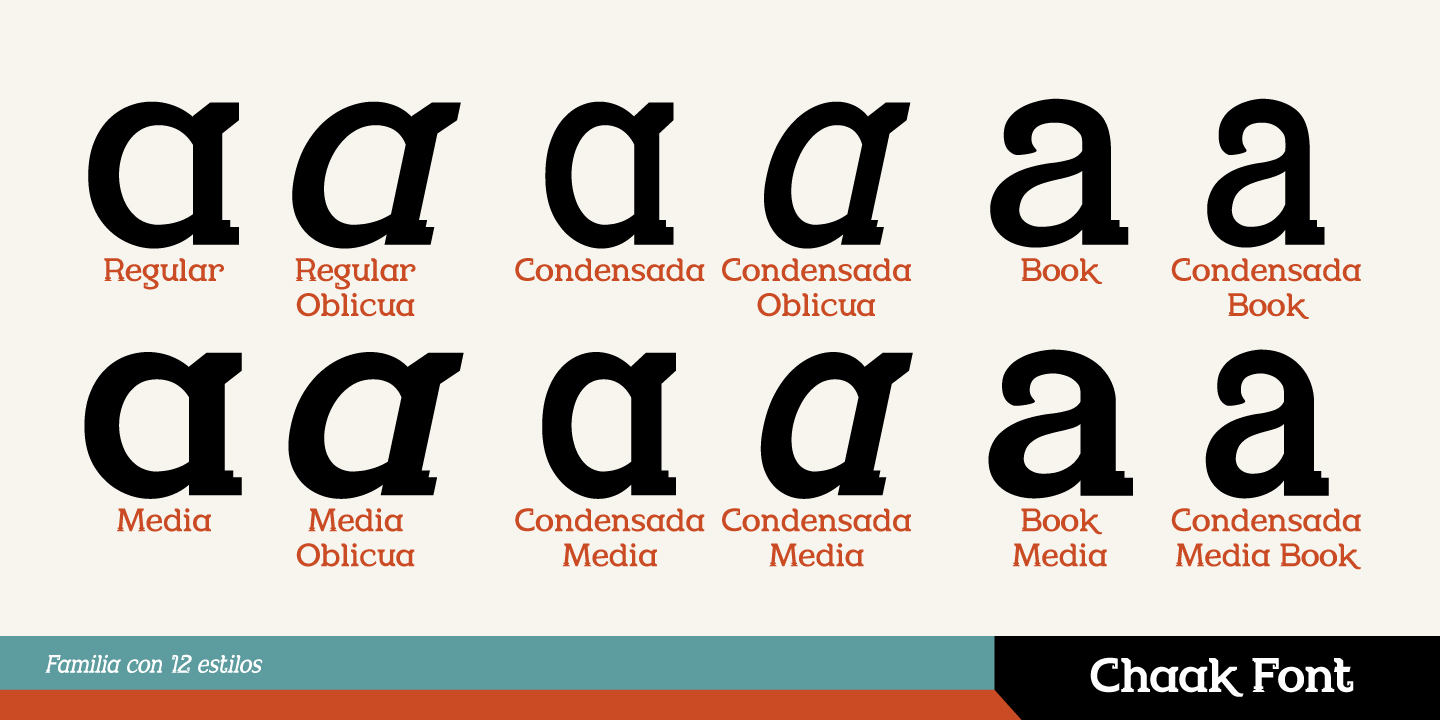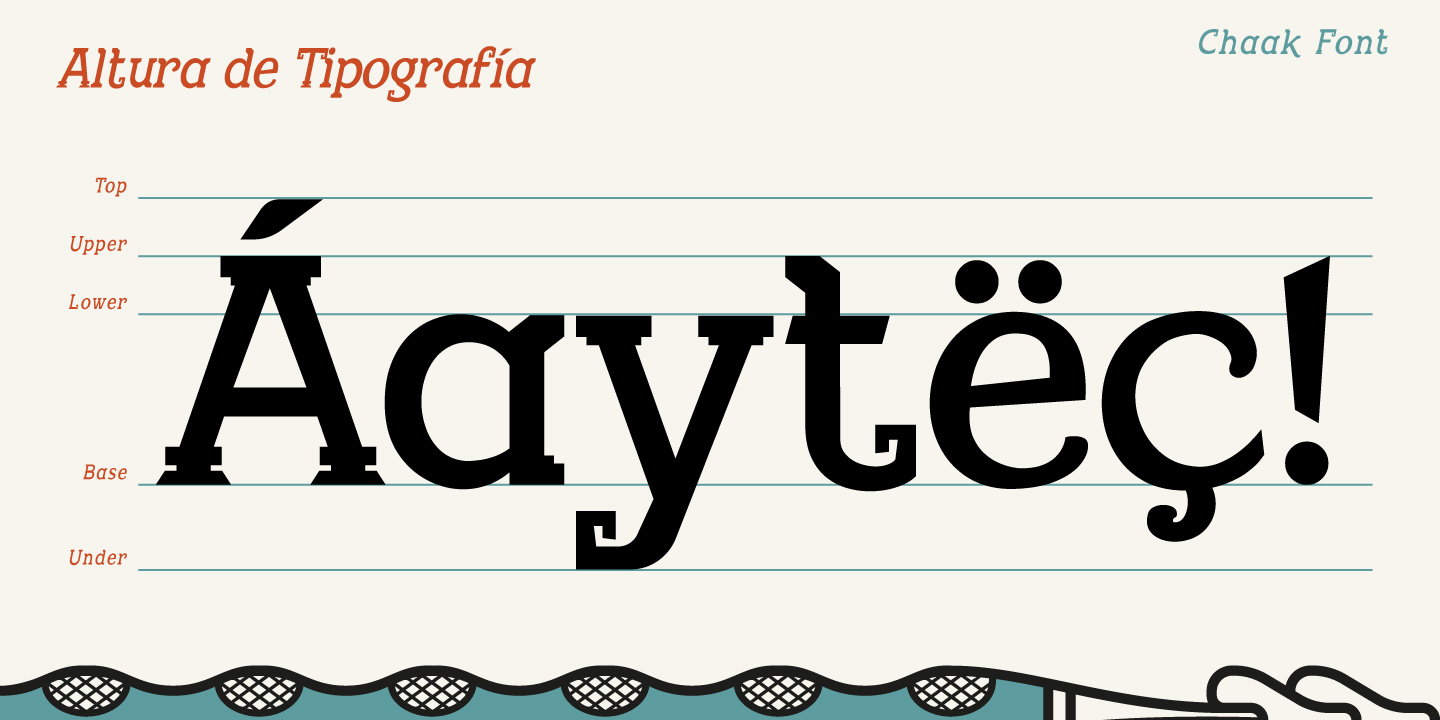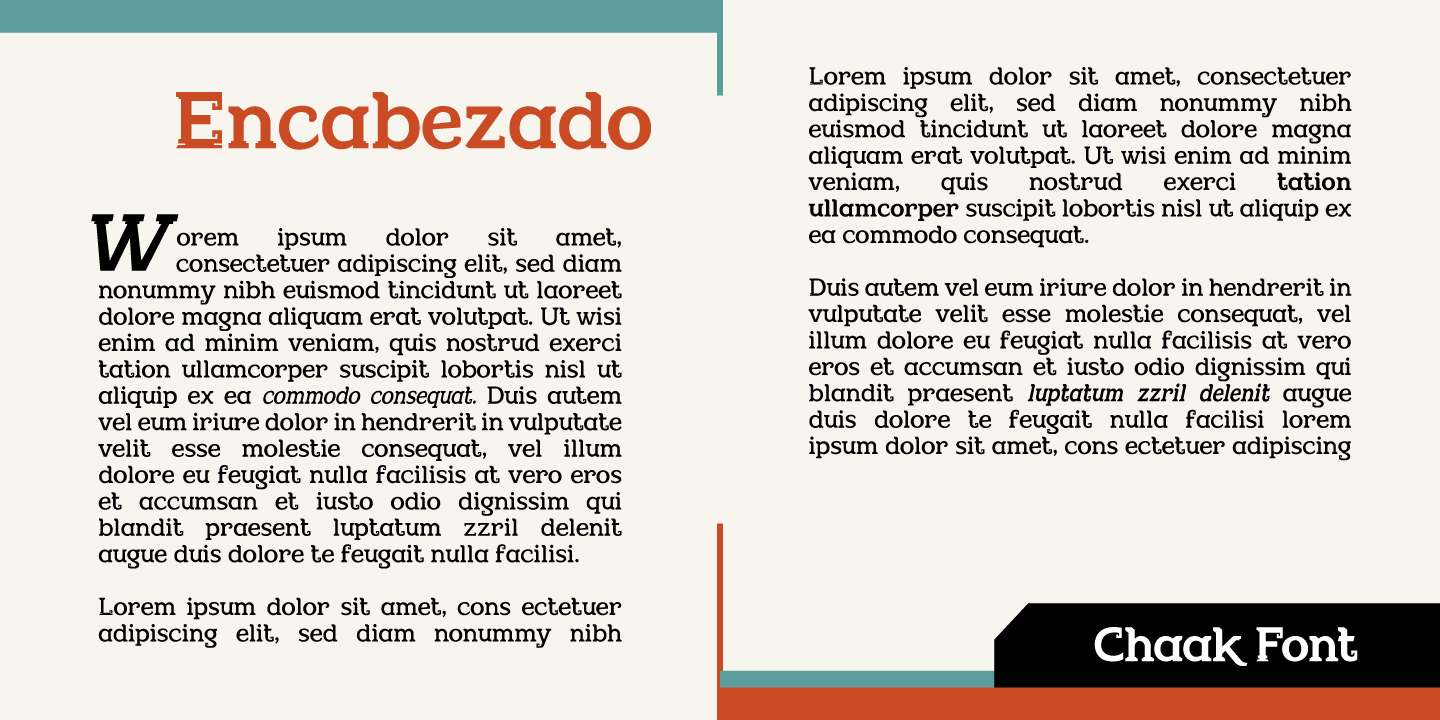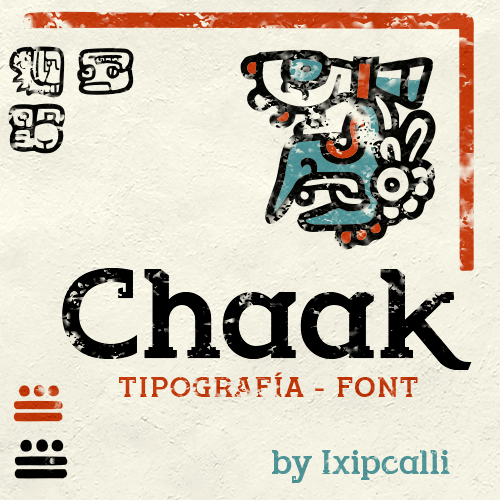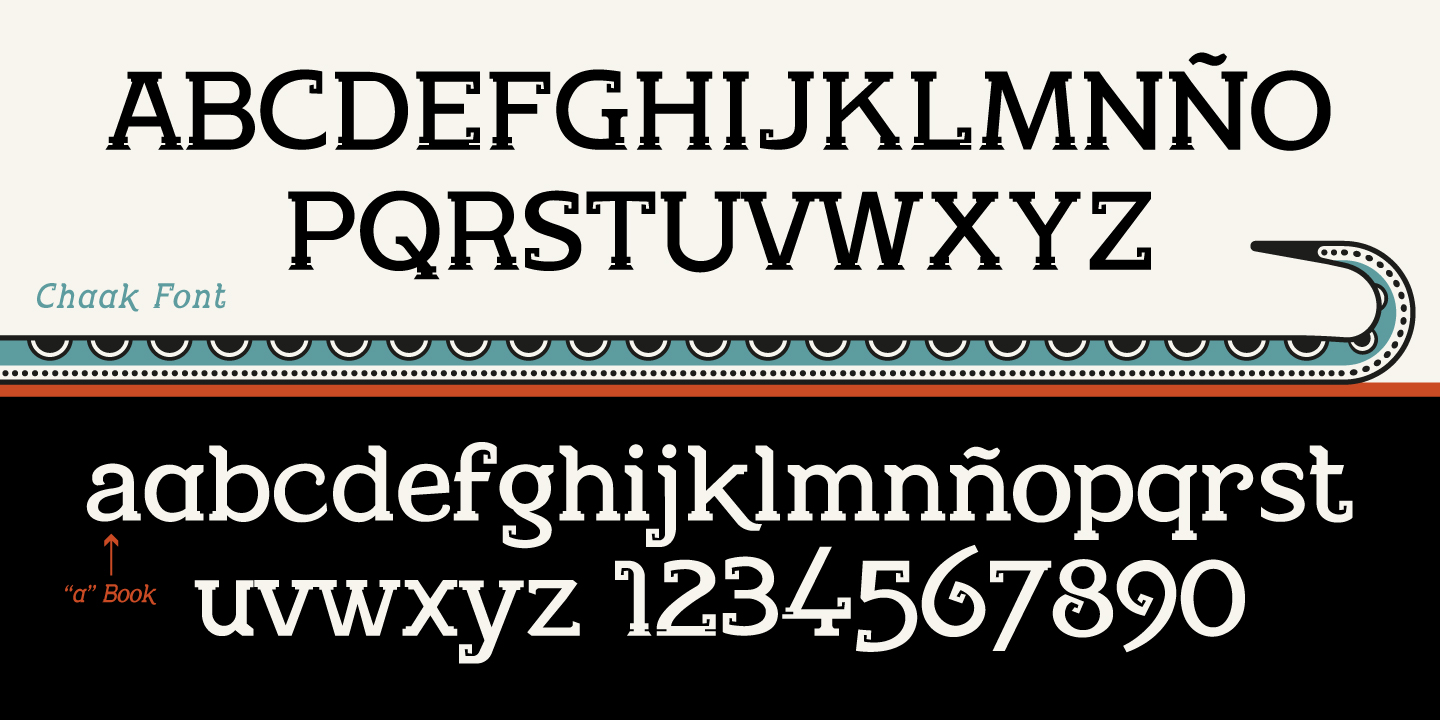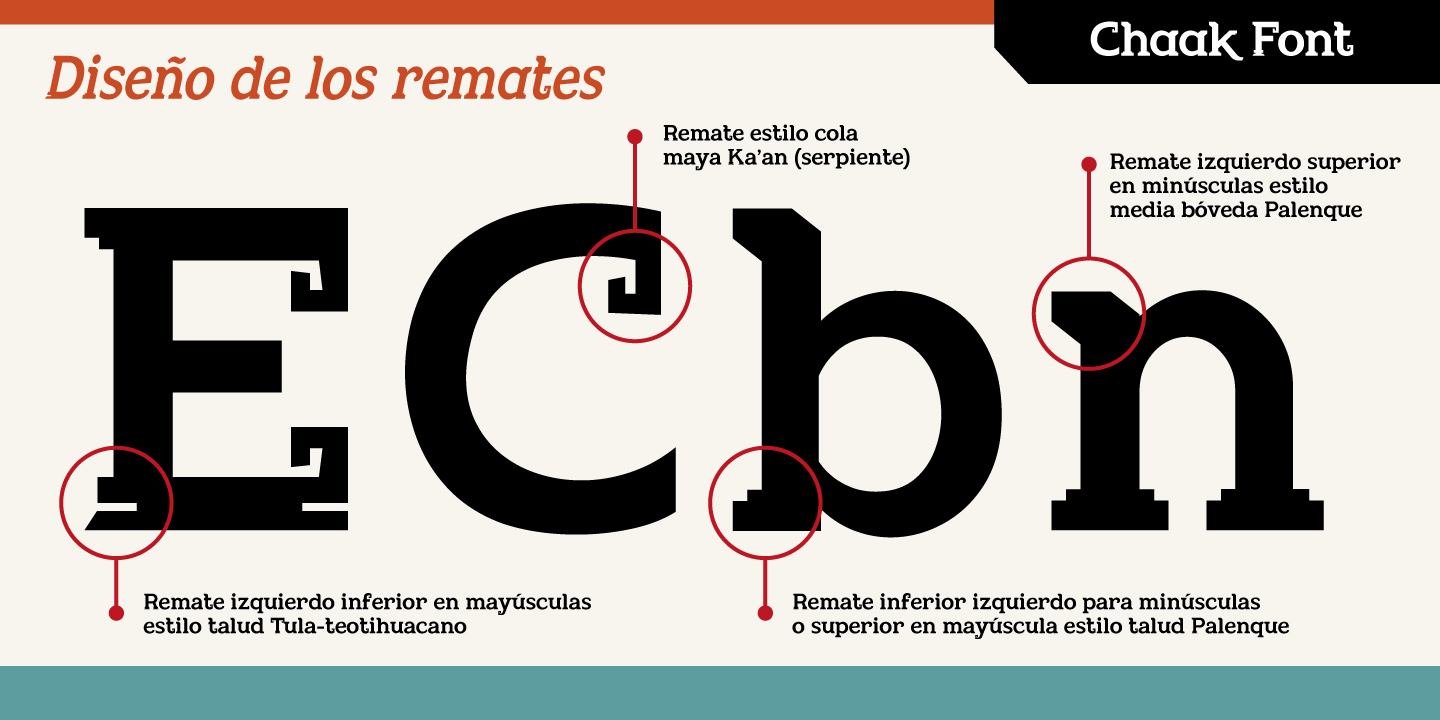
chaak
Descripción:
(2025) - La tipografía Chaak o Chaal Pro, se integra al catálogo temático de fuentes desarrollada como parte de proyectos de identidad, inspirada a partir de los estilos mesoamericanos mayas. Los remates inferiores de los tipos mayúsculas, aluden a los taludes de las bases y construcciones de los templos y edificios prehispánicos como aparecen en edificaciones mayas y teotihuacanas. Su nombre es adaptado al dios Cha’ak, señor de la lluvia y los relámpagos en el mundo maya.
La tipografía es de carácter Serif, añadiendo ocho estilos con dos pesos ligeramente visibles, “regular y media”. Además, incluye una variante de «a» alternativa para proyectos estilo book o comic. Cada peso y estilo presenta también su forma itálica y condensada para una mejor lectura.
La tipografía está perfectamente adaptada para uso en libros, escritos o cualquier documentación que requiera mostrar una forma semi formal, pero a su vez temática precolombina.